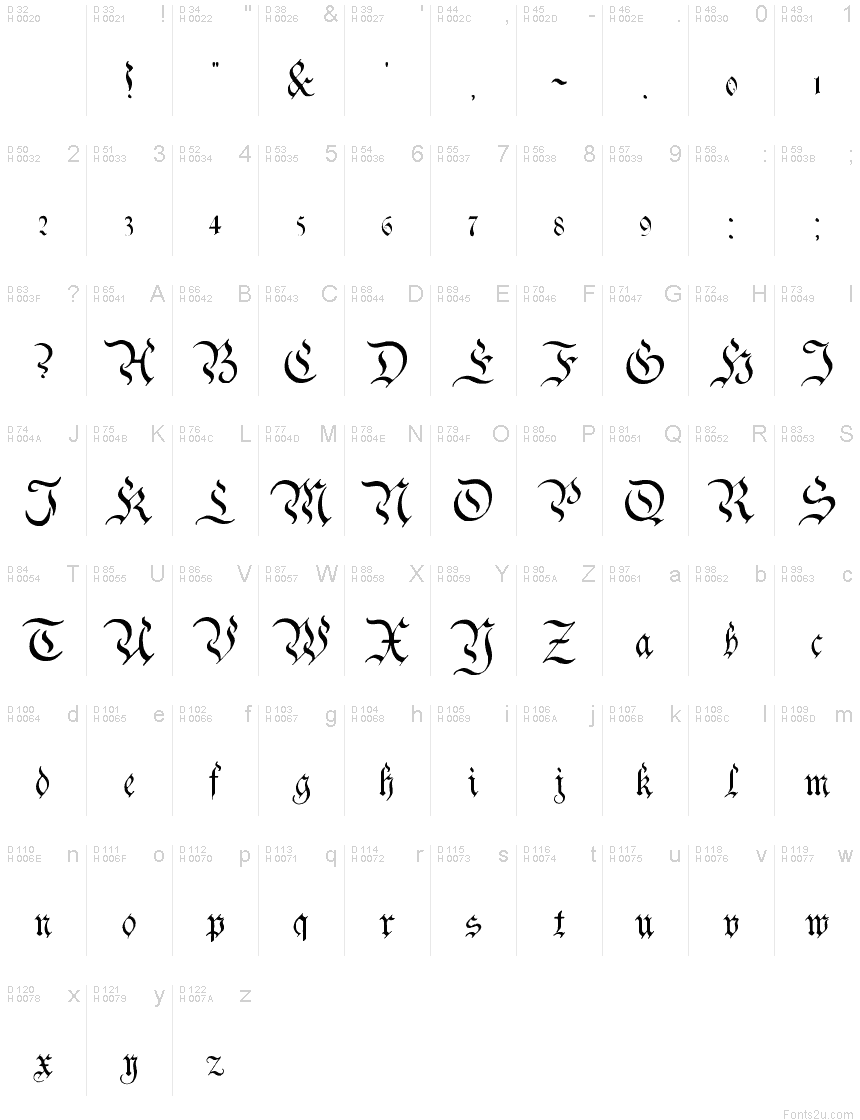
Charterwell od PJL to darmowy gotycki, średniowieczny krój pisma z atramentowymi, płomienistymi pociągnięciami oraz ostrymi, haczykowatymi krzywiznami, które wyglądają, jakby wyjęto je ze starej księgi zaklęć. Litery są gęste i dramatyczne, ze śmiałymi łukami i kolczastymi kątami, co nadaje im mocny, ręcznie kreślony rytm – niemal jakby zostały naniesione pędzlem na postarzany pergamin lub wykute w kamieniu.
Używając Charterwell, Twoje tytuły natychmiast przeniosą się w świat fantasy i folkloru, dlatego czcionka ta świetnie sprawdzi się w logotypach RPG, znakach graficznych zespołów metalowych, plakatach z jarmarków średniowiecznych, brandingu escape roomów oraz na okładkach książek z gatunku dark fantasy czy horroru. Ten darmowy font najlepiej prezentuje się w dużych rozmiarach; w tekście głównym połącz go z prostym bezszeryfowym krojem geometrycznym, aby zachować czytelność, podczas gdy Charterwell zadba o odpowiedni klimat.